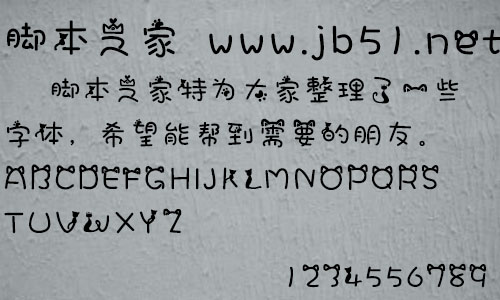
漢儀喵小姐簡由漢儀字庫出品的卡通字體,字體筆觸粗細(xì)適中,字體以貓咪元素進(jìn)行點(diǎn)綴,具有很好的視覺感,適合應(yīng)用于藝術(shù)設(shè)計(jì)、平面宣傳設(shè)計(jì)、網(wǎng)頁設(shè)計(jì),書法字帖等領(lǐng)域。有需要的朋友快來本站下載使用吧!